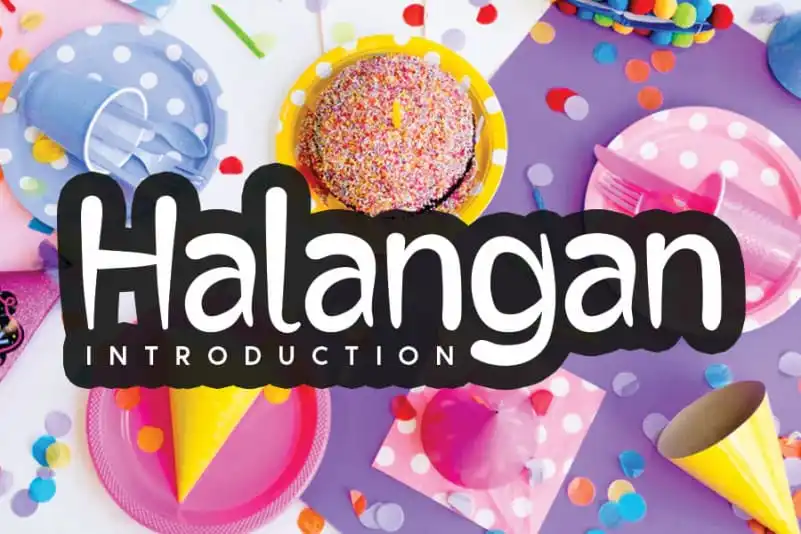
Halangan Display Font – Download Grátis
A fonte Halangan Display é uma seleção cuidadosa e meticulosa, criada para se tornar uma verdadeira preferência no mundo das fóntes display. Ela exibe um charme casual que a faz parecer natural, clara e extremamente versátil. Halangan brilha em qualquer contexto, seja ela usada sobre fundos ocupados ou como um título de destaque isolado. A sua elegância é perfeita para estilos modernos e atuais. Seja você designer ou profissional gráfico, a Halangan Display Font está pronta para ajudá-lo a destacar-se em qualquer projeto.